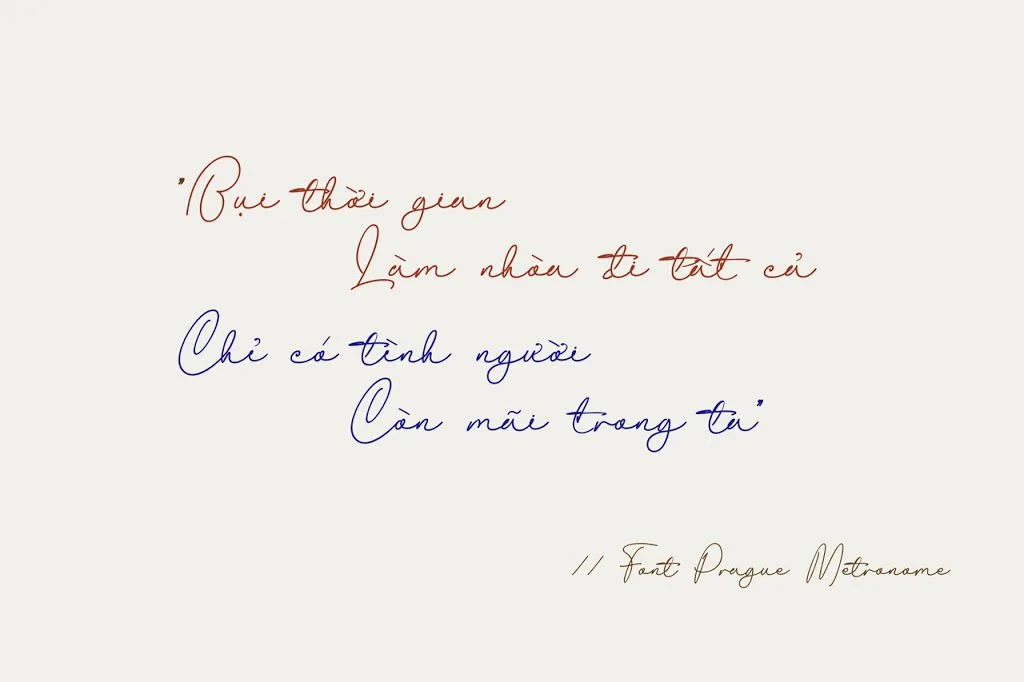
Font viết tay siêu đẹp Prague Metronome
Với phong cách viết tay đơn giản nhẹ kết hợp với những điểm nhấn nhẹ nhàng đã tạo nên font viết tay siêu đẹp Prague Metronome này.
Prague Metronome là một bộ Font viết tay siêu đẹp.
Bộ font viết tay việt hóa này được thực hiện bởi Đức Thủy. Font được vẽ dấu theo phong cách chữ viết Tiếng Việt nên tạo cho bạn cái nhìn quen thuộc hơn khi sử dụng.
Prague Metronome, một font viết tay tinh tế và đẹp mắt, tạo nên một trải nghiệm độc đáo và ấn tượng. Với sự kết hợp khéo léo giữa phong cách viết tay đơn giản nhẹ và những điểm nhấn tinh tế, Prague Metronome không chỉ là một bảng chữ cái mà còn là một tác phẩm nghệ thuật. Bức tranh chữ viết này như là bức tranh ngôn ngữ, mô phỏng sự hòa quyện giữa nét văn hóa cổ điển và sự hiện đại.